タイププロジェクト、フィットフォントサービスにGrilli Typeの欧文フォントを追加
タイププロジェクト株式会社(東京都練馬区 代表取締役社長 鈴木 功、以下タイププロジェクト)は、本日、フィットフォントサービスに新しくGrilli Typeの欧文フォントを追加したことを発表いたしました。
Grilli Typeは、スイス中部のルツェルンを拠点にグローバルに活動するフォントファウンダリーで、多言語フォントの制作、グローバルブランドのためのカスタムフォントファミリーのデザイン、オリジナルの文字商標のデザインなど、書体に関係するプロジェクトを幅広く行っています。
フィットフォントは、タイププロジェクトのサイトのスライドバーによりウエイトや字幅を調整することで、モニタのサイズやディスプレイの解像度、広告やカタログなど使用目的に合わせた最適なフォントをご注文いただけるサービスです。独自開発技術により、ウエイトやコントラスト、字幅を変更した場合でも、字画の比率が適正で常にバランスの取れた状態を保ち、ダイナミックに変化しながらもデザインの一貫性と品質を保持することを実現しています。
今回、フィットフォントサービスに追加したGrilli Typeの欧文フォントは、GT Alpina、GT America、GT Super、GT Sectra、GT Zirkonの5ファミリーで、全36フォントです。
Grilli Typeの創業者の一人であるNoël Leu氏は、「私たちは、主張のある書体をデザインしています。同時に、フォントは機能性も備えているべきだと考えているので、技術的にも非常に優れたフォントになっています。フィットフォントは、欧文と和文フォントの組み合わせとして最適な方法だと思います。手を加えずにそのまま欧文フォントと組み合わせることも、プロジェクトの要件に合わせてさまざまなレベルでカスタマイズすることもできます。タイププロジェクトとパートナーになれたことに、心から感謝しています。」と述べています。
■ 組合せ例
GT Alpina Standard Regular + TP明朝フィットフォント
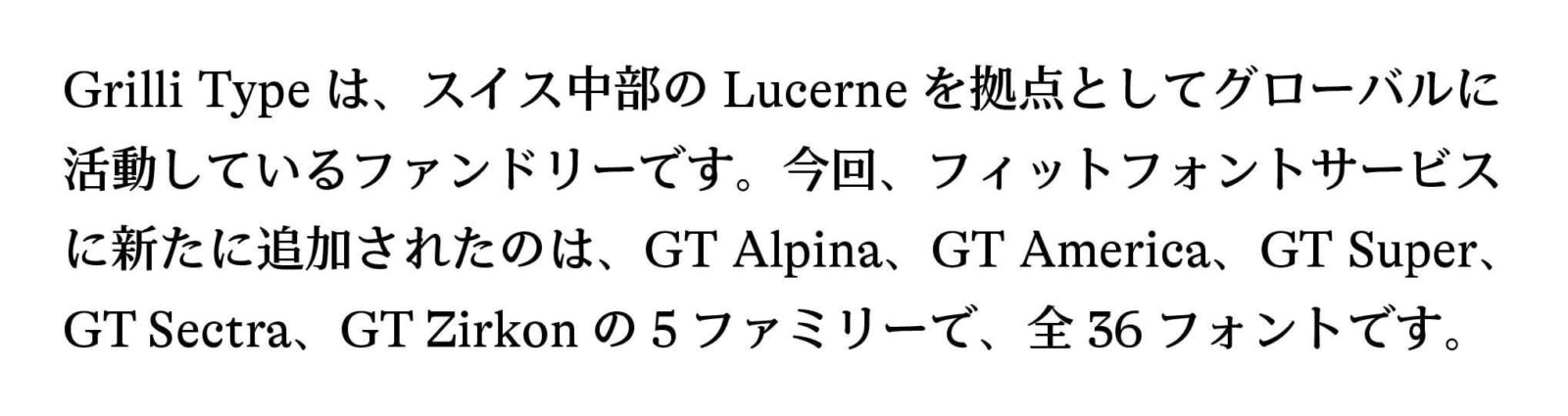
ブランドの声としての役割を果たすタイプフェイス / Grilli Type